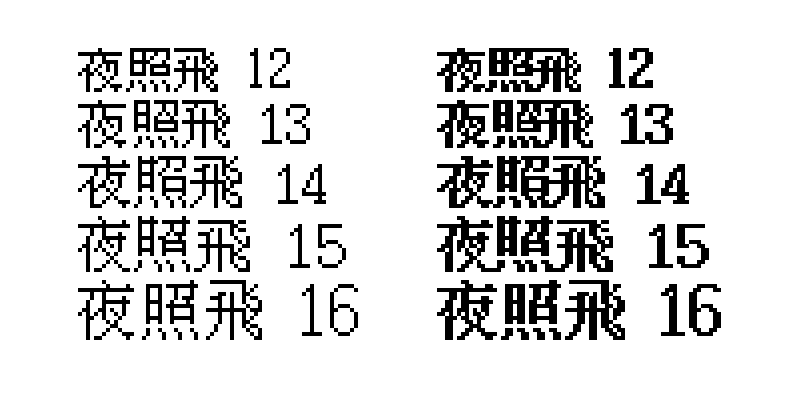
夜照飞(Nightgazer)字体系列是在萤火飞(FireFly)的 bdf 点阵字体基础上进行修改而来的 TTF 点阵字体。每款字体大约包含 17,300 个字符,主要使用繁体中文字形,同时支持繁体中文、简体中文、西里尔字符、日文字母等。
夜照飞字样,编号12至16
简介
这种点阵字体格式来源于“螢火飛 bdf”字体。通过 GPL 许可协议,该字体格式被转换为 TTF 格式,之后对一些难以辨认的常用符号进行了一些修改。
• 2026 年 3 月 11 日:更新了粗体字重样式。此时,“夜照飞点阵字体系列”共有 5 种尺寸规格,每种规格包含 2 种字重,总计 10 种款式。